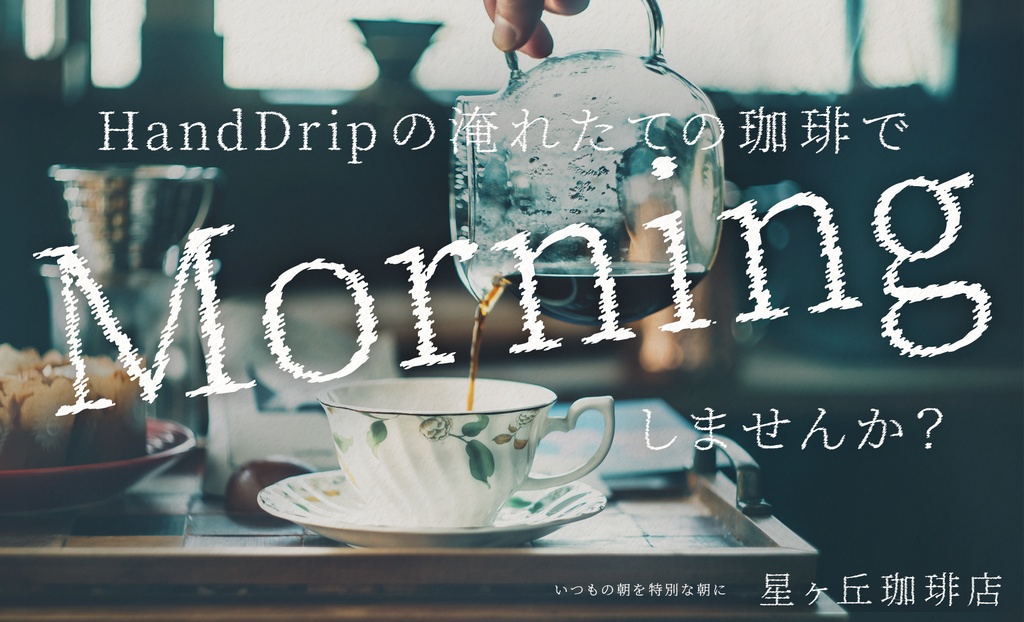
瞬きノ明朝
“瞬きノ明朝”是一款挺特别的字体,名字直译是“眨眼的明朝体”,听起来就有点意思。它的设计灵感来自日本的开源字体“源ノ明朝”(Source Han Serif),但加了独特的处理——字形边缘有点像被抖动过,带着一种模糊的、瞬间移动后的残影感。整体看过去,既保留了明朝体的优雅,又多了一份动态和不规则的趣味。
这款字体是 Flop Design 开发的,收录了8000多个字符,覆盖日常用字没问题。它的笔画在粗细上有点变化,放大用的时候特别显眼,像是有种跳动的生命力,很适合做标题、logo 或者海报设计;缩小用的话,又有点像粉笔字被轻轻擦过的复古味儿,挺有层次感。我觉得它在视频字幕或者创意印刷品上应该会特别出彩,能一下子抓住人的注意力。